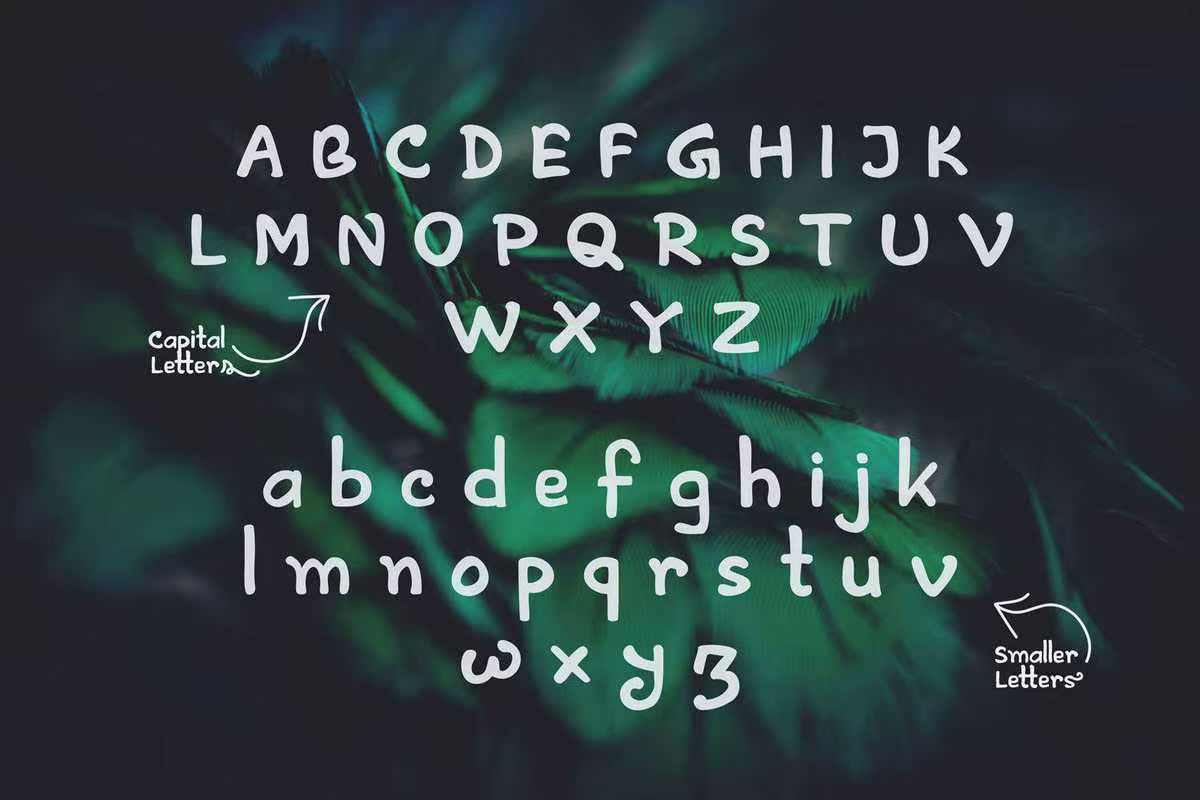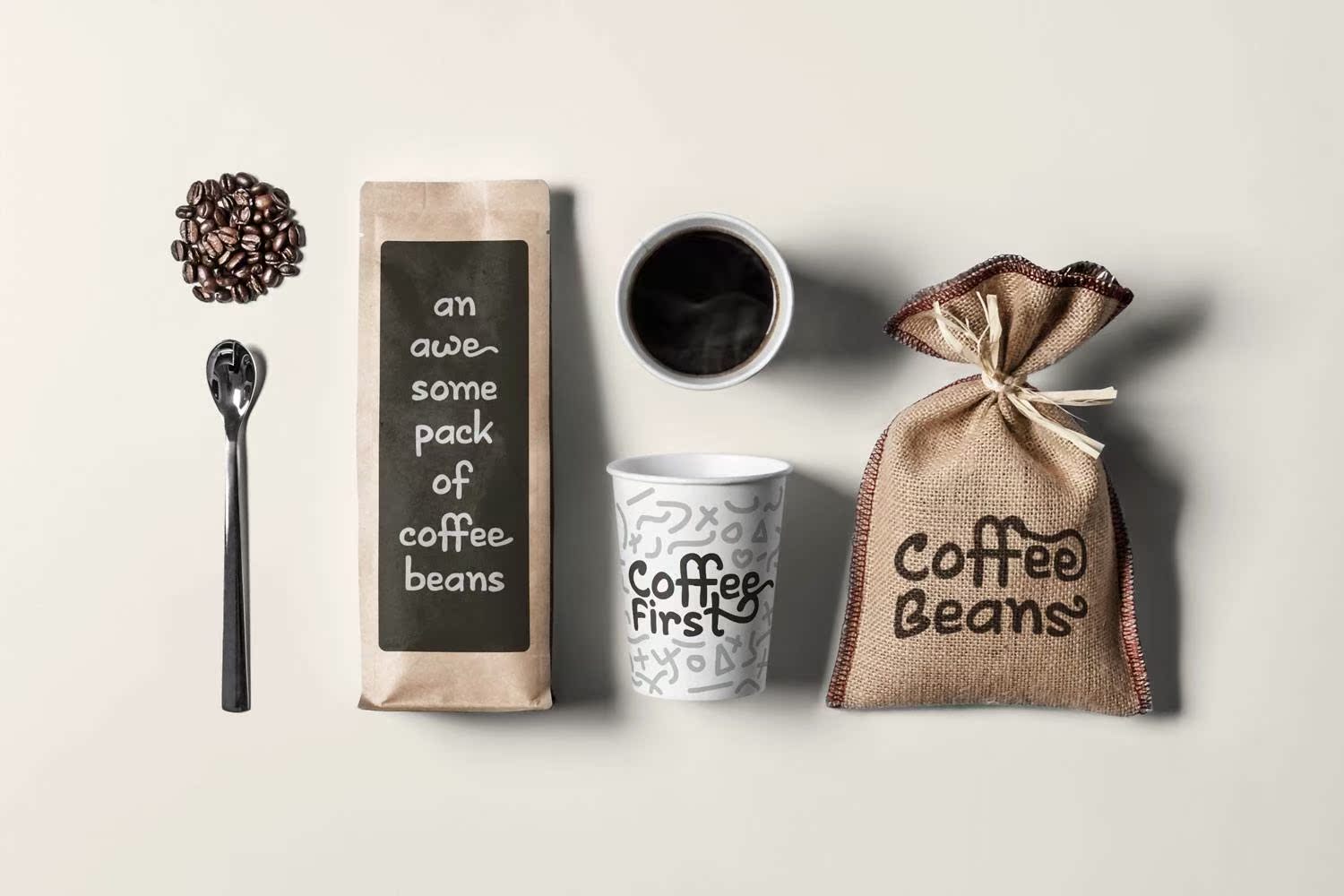
Artless,AbeautifullyCraftedHandwrited,bold,modernlookingscriptfont。共246个字形:A-Z,A-Z,0-9,多语言字符,货币符号,标点符号,交替,很快。用激情创建,从纸张到数字屏幕再到InstallableFontFile。完整版本有OpenType,TrueType和WoffWebFontFiles。Artless,AbeautifullyCraftedHandwrited,bold,modernlookingscriptfont.Ithastotal246字形:A-Z、A-Z、0-9、多语言字符、货币符号、标点符号、替代符号等等。用激情创建,从纸张到数字屏幕再到安装字体文件。完整版本有OpenType、TrueType和WOFFWebFontFile。